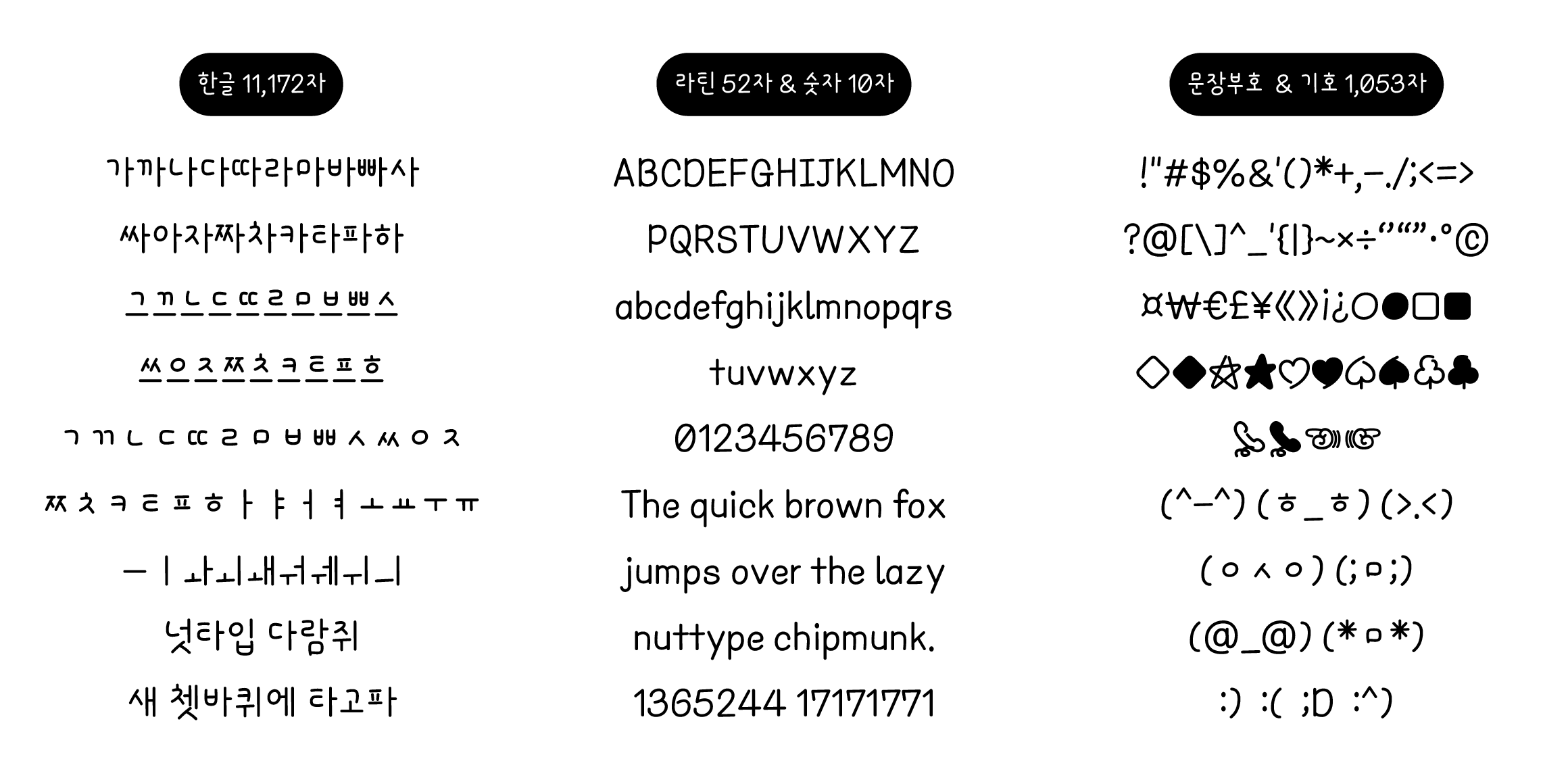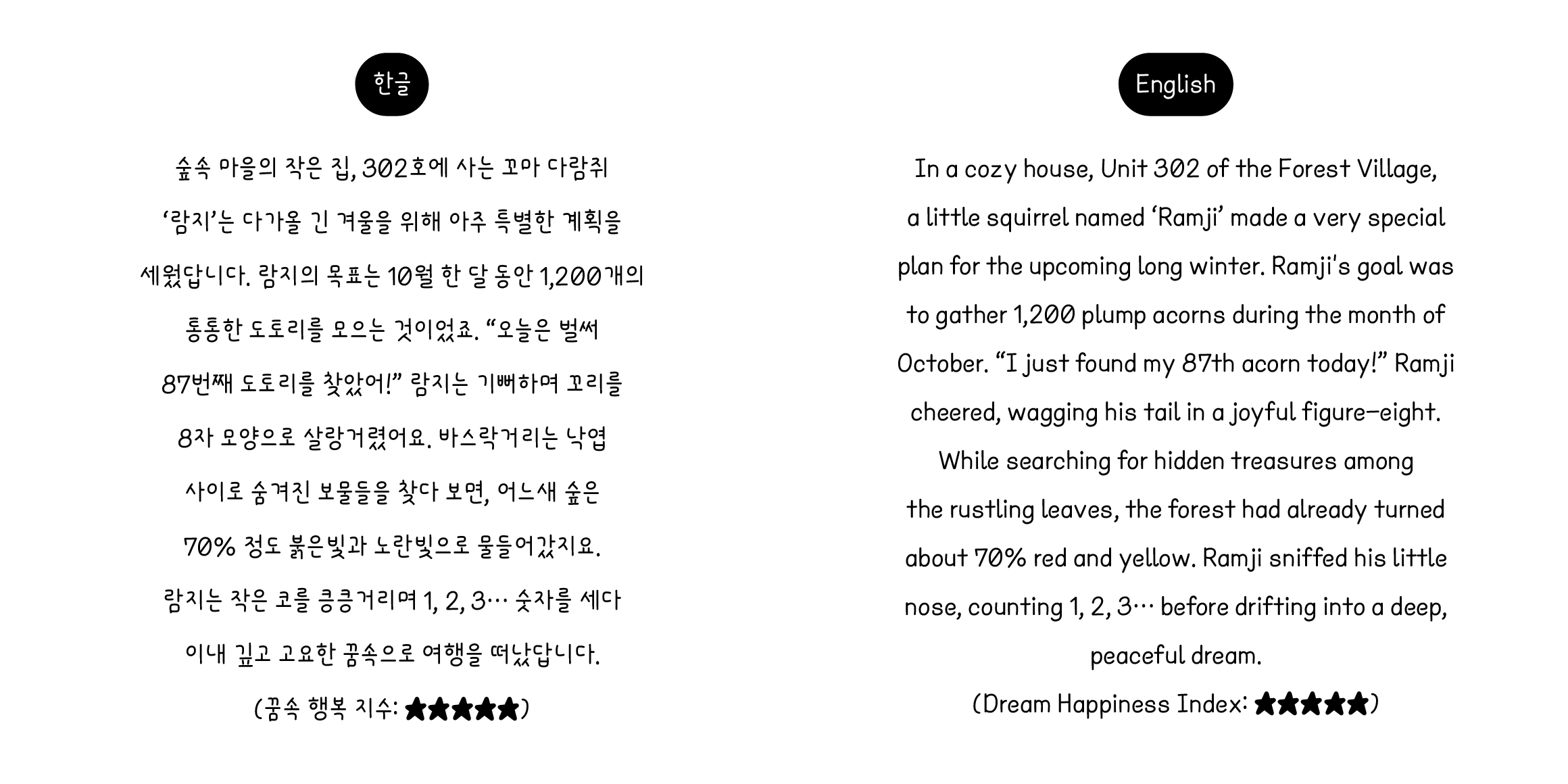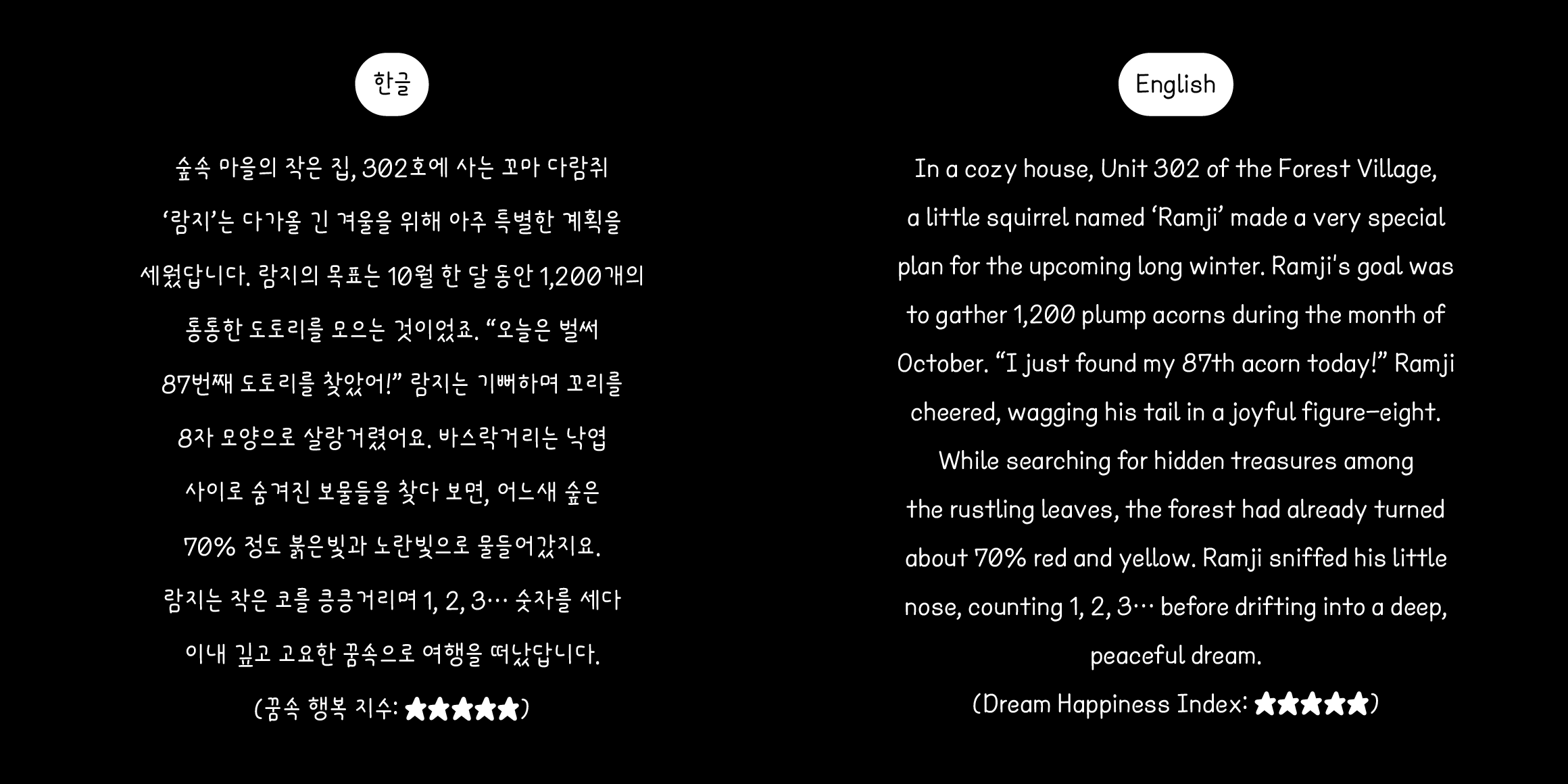
nut 토마토람지
Nuttype
분류 Script,손글씨
제목용영상개성적
오늘 날씨 앱을 세 번 확인했는데, 세 번 다 틀렸다. 나갈 때 덥고, 들어올 때 춥고, 바깥에서는 더운데 그늘에선 으슬으슬했다. 아이스 아메리카노를 들고 나왔는데 십 분 만에 미지근해졌다. 얼굴은 빨갛고, 머리는 뜨겁고, 기분은 묘하게 나쁘지 않다. 토마토람지는 어차피 여름엔 다들 빨개지니까 이 계절이 제일 마음이 편하다. 드디어 평등해졌다.
• Script,손글씨
• nut 토마토람지 / nut Tomato Ramji
• 제목용,영상,개성적,유쾌한,귀여운